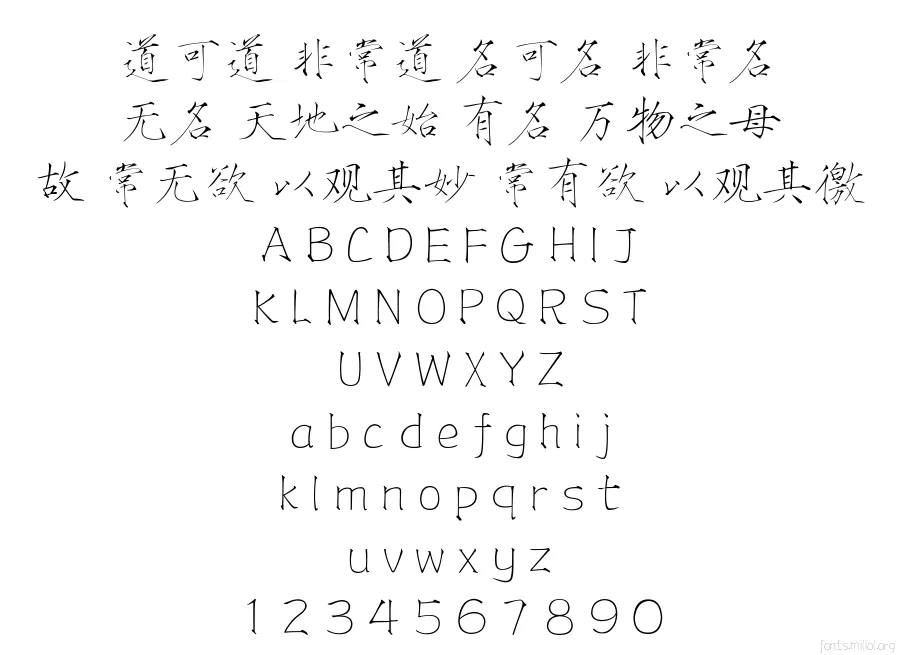
## 方正瘦金书_GBK:传统书法艺术的数字新生
方正瘦金书_GBK字体完美再现了宋徽宗独创的瘦金体书法精髓,将千年传统艺术带入数字时代。这款字体以瘦劲挺拔的笔触著称,横画收笔带钩,竖画收笔呈点,撇如匕首,捺似刀锋,完美保留了原书体的独特韵味。其GBK编码体系支持繁简体中文及多种特殊字符,确保在各类文档中都能流畅显示。设计师们常将其运用于文化类海报、书籍装帧等场景,既能传递古典雅致的美感,又不失现代设计的简洁。作为方正字库的重要成员,这款字体严格遵循汉字书写规范,每个字符都经过书法专家与字体设计师的反复推敲。在数字化阅读日益普及的今天,方正瘦金书_GBK让传统文化以新的形式延续生命,为现代视觉设计提供了兼具历史底蕴与艺术表现力的字体选择。
方正瘦金书_GBK 字体映射图